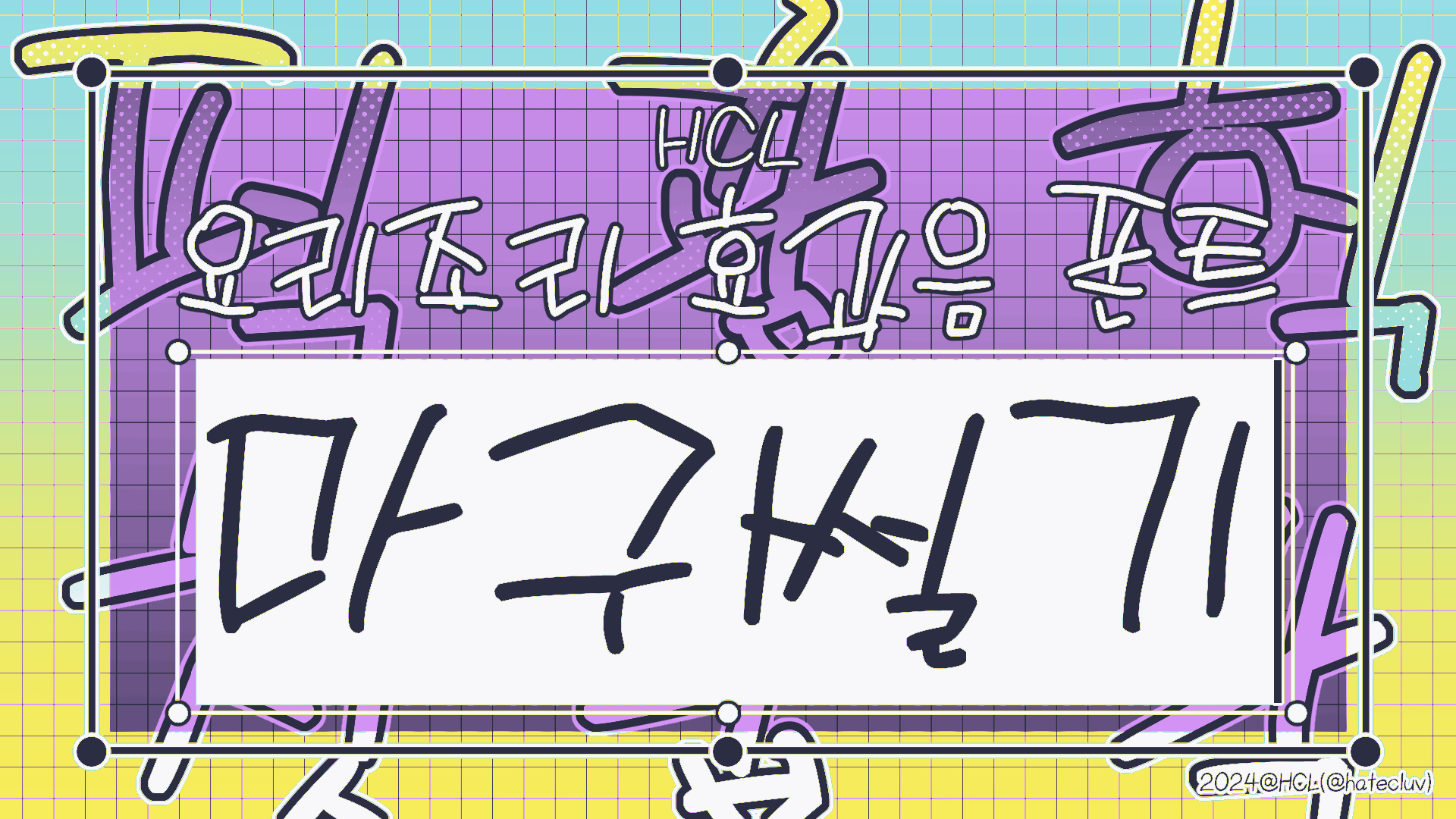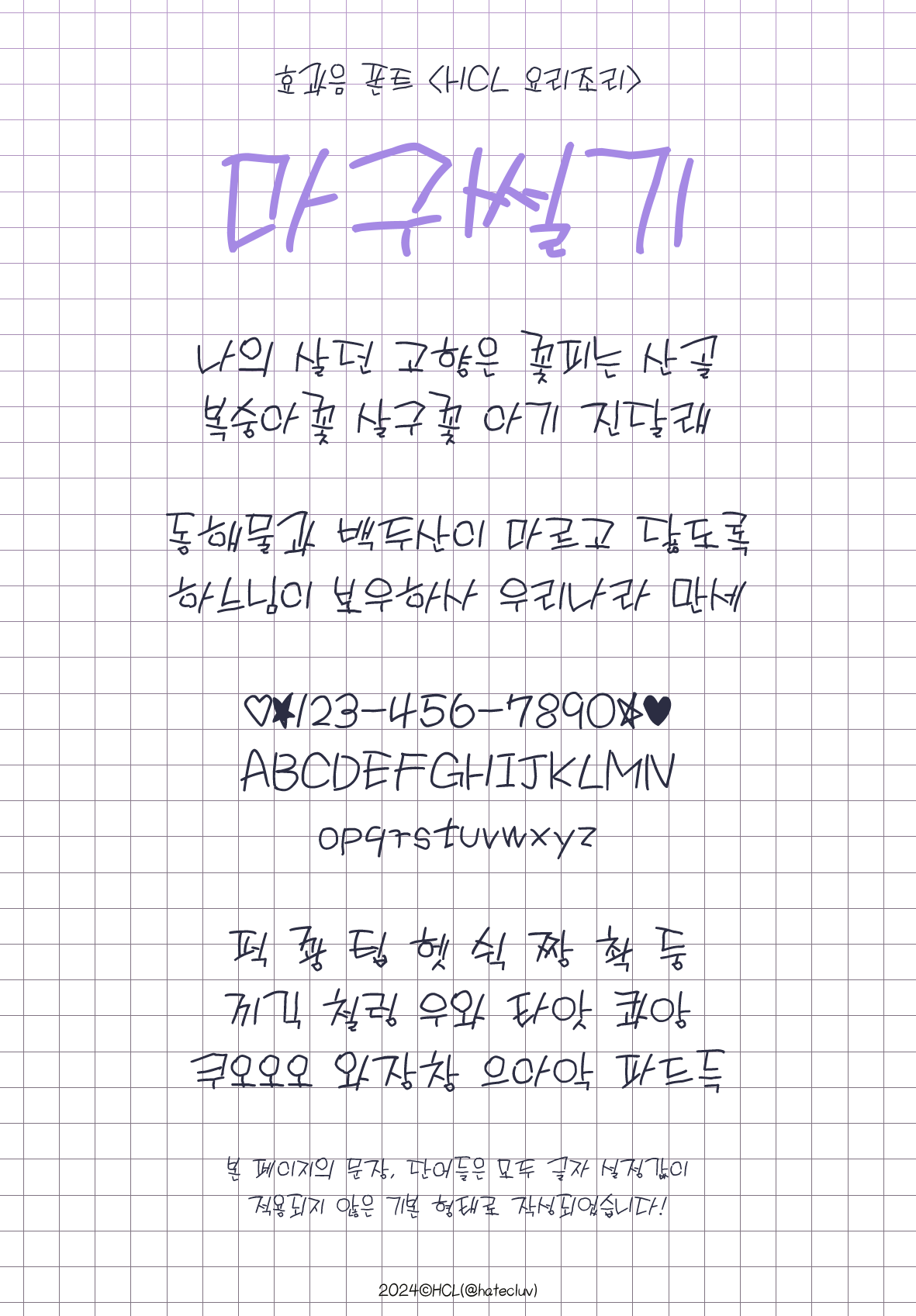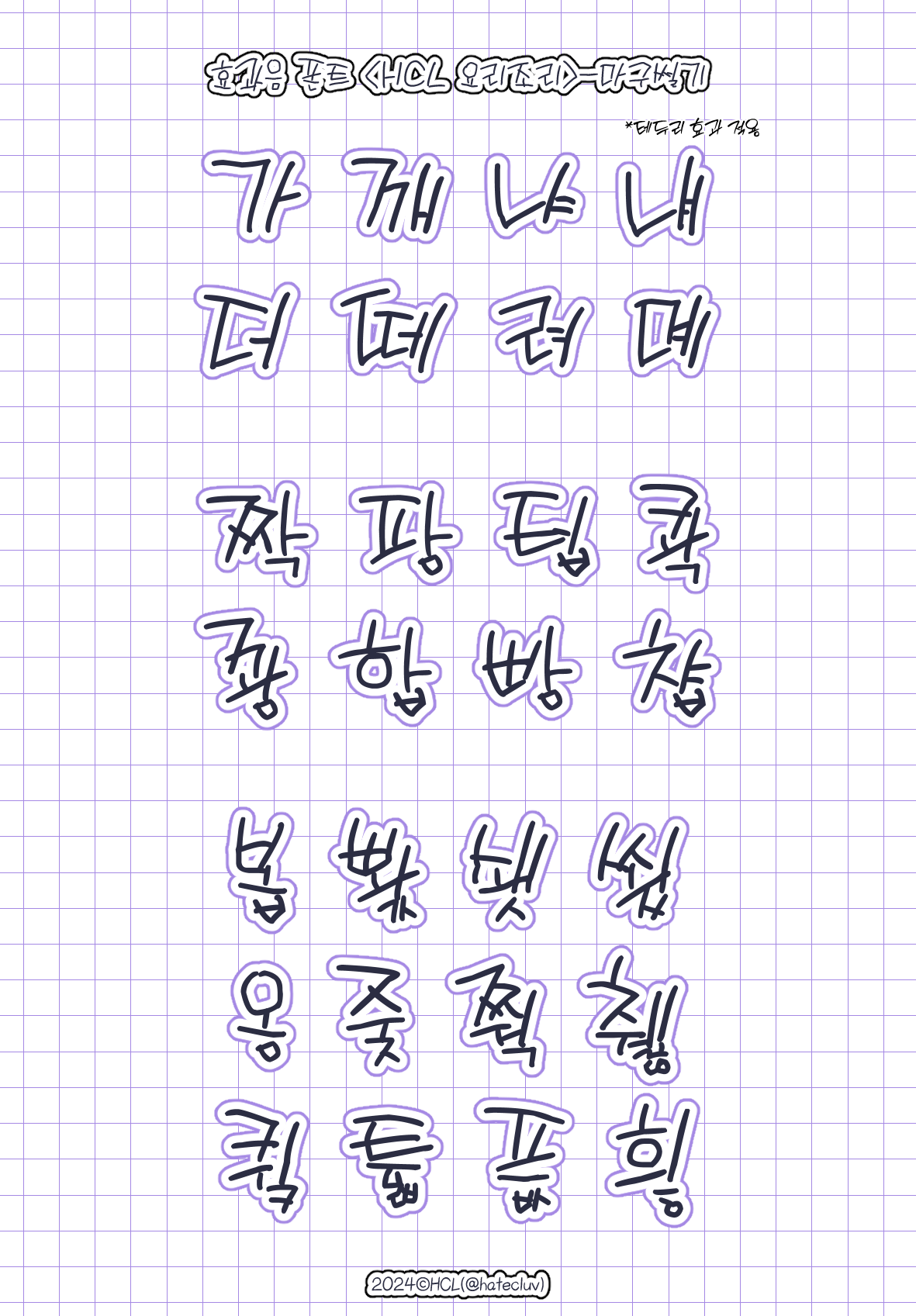
만화 효과음 느낌의 캘리그라피 폰트 5종 시리즈 <HCL 요리조리> 중 <마구썰기> 입니다. 어색한 / 당황한 / 안절부절못하는 등 특정 분위기의 효과음 연출과 말풍선 근처 작은 대사 용으로 제작한 글꼴입니다.
한글 조합 11172자 전체, 한글 기본 자모음(ㄱ,ㄴ,ㄷ,ㅏ,ㅑ,ㅓ...) 52자와 영문 대소문자, 숫자, 키보드 쉬프트 특수문자, ☆★♡♥, ©(카피라이트 문자) 등 추가 120글자를 지원합니다.